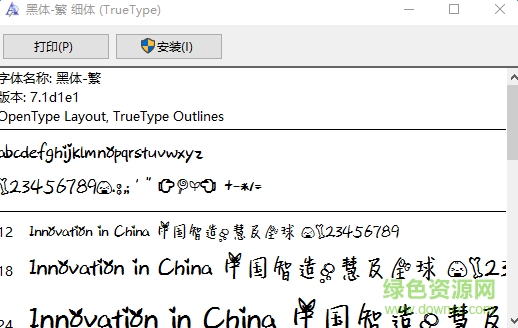
涼如三月
涼如三月字體是一款很有特色的電腦藝術(shù)字體,這款字體寫出來的字是很好看的,特別是用于藝術(shù)寫作或者是廣告設(shè)計都是很不錯的,喜歡的朋友可以隨時來綠色資源網(wǎng)下載。
涼如三月字體這款字體是真的很不錯,不僅字形特別美,還特別實用,可以用在很多方面,喜歡的朋友就快來綠色資源網(wǎng)下載吧。